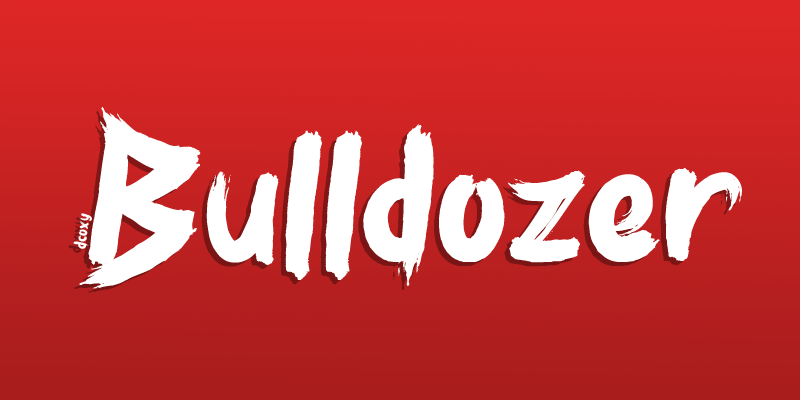
A Bulldozer Font é uma elegante seleção de letras brush que surge com um toque moderno e vibrante. Ela foi criada pelo designer Hamilton para aqueles que procuram uma fonte única capaz de destacar a sua marca ou projeto. Com linhas finas, pontas aparentes e traços ágeis, essa fonte é perfeita para usar em design gráfico moderno, desde logotipos até trabalhos web responsivos. Se você deseja adquirir esta fonte para uso comercial ou promocional, por favor, entre em contato com Hamilton antes: . Ele estará à disposição para fornecer informações e auxiliar na utilização da sua nova escolha. Sua fonte agora pode trazer um toque único e moderno ao seu trabalho, tornando-o ainda mais impressionante.